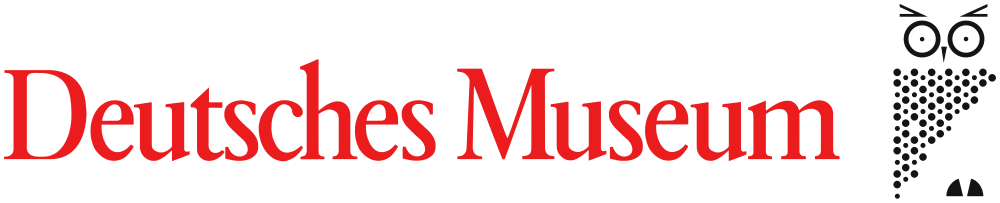
Schrift im Logo des Deutschen Museums
es mag mir nicht gelingen herauszufinden, welcher Schrift das Logo des Deutschen Museums entstammt. Garamond ist nah, scheint aber nicht identisch (das Logo läuft recht schmal). Wer kann helfen?
Die Berthold Garamond Condensed ist schon sehr nah dran aber kleine Details stimmen eben doch nicht. Weißt du von wann das Logo ungefähr ist?
Leider nein. Ich kann bisher nichts Vernünftiges zur Historie des Logos selbst finden.
Aber gerade die Tatsache, dass es eben in den Details (die für das Logo anzupassen mir ein wenig irrsinnig erscheint) nicht auf die Garamond passt, verwundert mich. Dennoch danke für jede Idee.